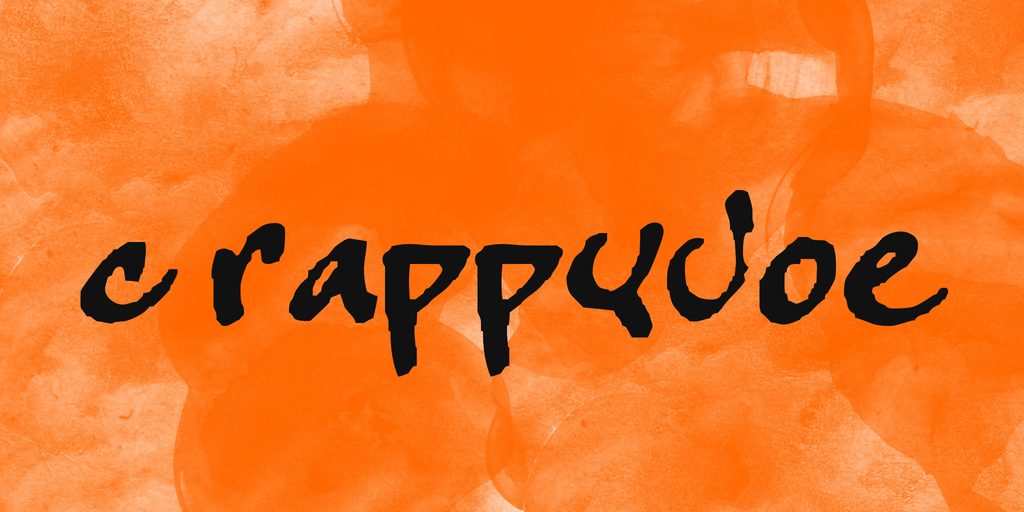
crappyJoe Font – Fonte Grátis
crappyJoe Font
A fonte CrappyJoe é uma criação experimental e única do designer Hamilton, perfeitamente adaptada para quem busca algo despretensioso e não oficial em suas criações digitais. Com linhas levemente borradas e texturas irregularmente espalhadas, a CrappyJoe oferece um toque casual que se torna bastante reconhecível quando você inicia qualquer projeto criativo. Seja para criar mensagens pessoais ou até mesmo cartões de aniversário, essa fonte despojada não só adicionará um charme único ao seu trabalho, mas também deixará uma impressão indelével em seus destinatários. Ideal tanto para as camadas mais sombrias quanto para aquelas que buscam diversidade e originalidade, a CrappyJoe é certamente uma escolha inegável para qualquer criador de conteúdo digital em busca de algo único.